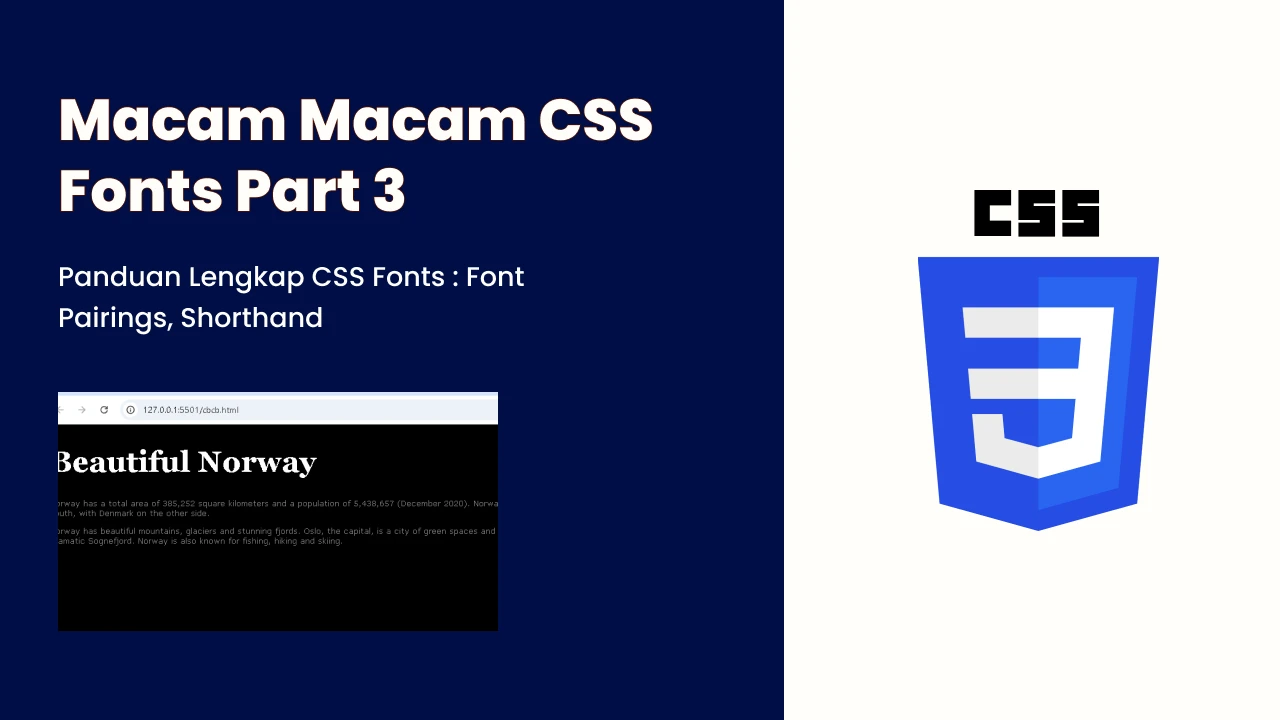
Pastikan font yang digunakan memiliki keserasian—tidak terlalu mirip, tetapi juga tidak terlalu berbeda.
Superfamily adalah sekumpulan font yang dirancang untuk bekerja sama dengan baik. Misalnya, keluarga font Lucida memiliki beberapa variasi seperti:
Menggunakan font dari satu superfamily memastikan keserasian yang lebih baik.
Menggabungkan dua font yang terlalu mirip bisa membuat desain tampak monoton. Kontras yang baik akan membuat masing-masing font lebih menonjol.
Contoh: Menggabungkan serif (font dengan hiasan pada huruf) dengan sans-serif (font tanpa hiasan) adalah kombinasi yang umum.
Gunakan satu font sebagai "bos" atau font utama untuk memberikan hierarki pada teks.
body {
font-family: Verdana, sans-serif;
font-size: 16px;
color: gray;
}
h1 {
font-family: Georgia, serif;
font-size: 60px;
color: white;
}
berikut hasilnya
1. Georgia + Verdana
2. Helvetica + Garamond
Jika ingin menggunakan lebih banyak pilihan font, bisa memakai Google Fonts, yang memiliki lebih dari 1000 pilihan font gratis.
Beberapa kombinasi populer:
Setiap kombinasi ini memiliki karakteristik unik yang cocok untuk berbagai jenis desain.
?Properti font adalah shorthand property (penulisan singkat) yang menggabungkan beberapa properti font dalam satu deklarasi.
Properti yang bisa digabung dalam font
Contoh Penggunaan
p.a {
font: 20px Arial, sans-serif;
}
Pada contoh ini:
p.b {
font: italic small-caps bold 12px/30px Georgia, serif;
}
Pada contoh ini:
berikut hasilnya